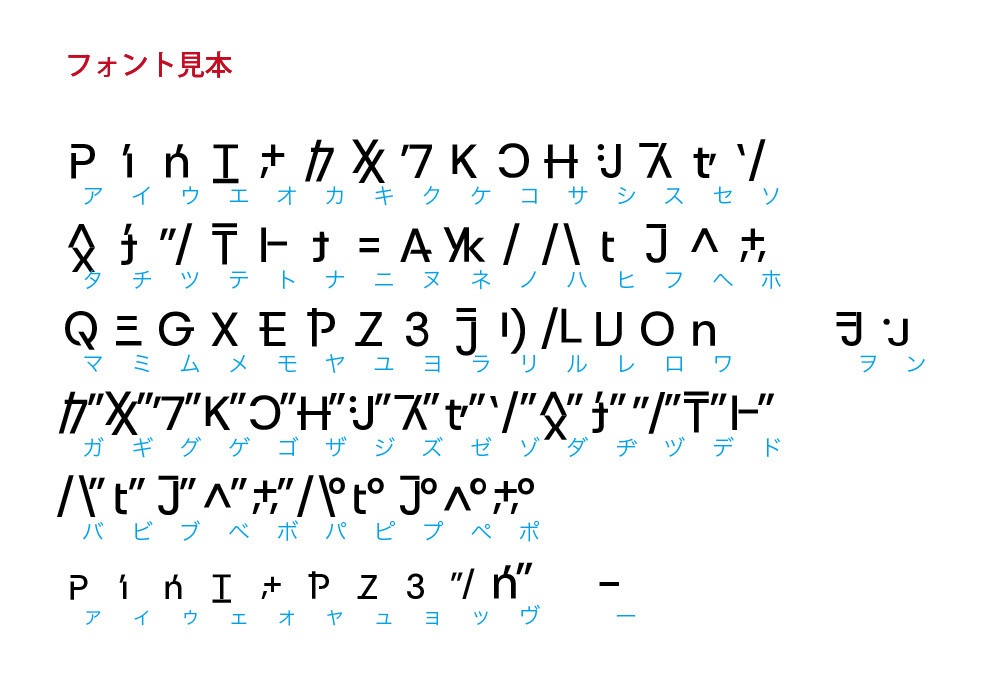
デジタルコンテンツ ラテン文字っぽいカタカナフォント
英語やラテン語などに使われているラテン文字っぽくデザインしたカタカナフォントです。 一見すると英語で書かれたようにも見えます。 基本的に横書き用です。縦書きにした場合、促音・拗音・長音の位置が横書きと変わらないので違和感が生じます。 【収録文字】 アイウエオカキクケコサシスセソタチツテトナニヌネノハヒフヘホマミムメモヤユヨラリルレロワヲン ガギグゲゴザジズゼゾダヂヅデドバビブベボパピプペポ ヴ ァィゥェォャュョッ 長音(ー) 【データ内容・使用方法】 zipファイルを解凍してください。 OTFファイル pklatinkana-Regular.otf JPGファイル(カタカナ表示の見本) sample.jpg テキストファイル readme.txt が収録されています。 pklatinkana.otf をインストールしてください。 【購入の際の注意点】 商用利用OKです。 使用した場合、ご一報いただけるとうれしいです。X(旧Twitter)などで紹介します。 フォントファイルの改変・再配布は禁止です。